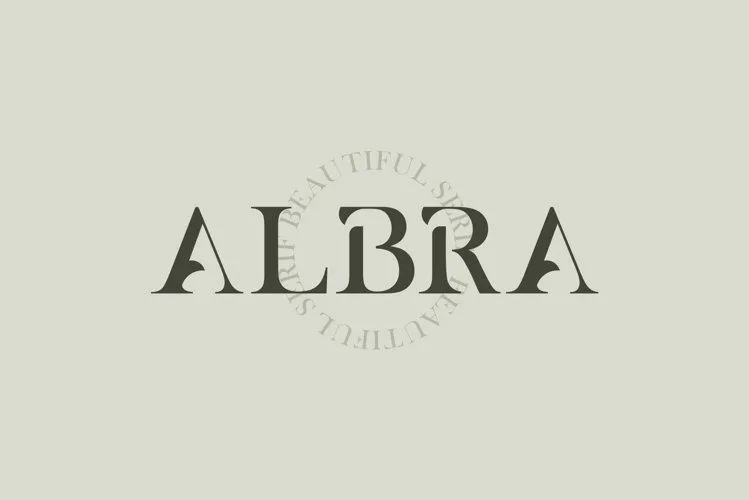
A Albra Font é uma tipografia serif inspirada nas kana hiragana, criada pelo designer Vroz Studio. Esta fonte é perfeita para uma variedade de projetos, desde editoriais e revistas até invitations de casamento e postais de aniversário. Ideal para se adequar a estilos variados como moda, branding, fotografia e design de blog. A Albra Font também brilha em aplicativos digitais, tais como websites e blogs. Seja você um designer gráfico ou editor de fotos, a Albra oferece flexibilidade para personalizar e adaptá-la a diversas necessidades. Além disso, sua elegância e detalhes sutis garantem um toque refinado a qualquer projeto que escolha aplicar. Compreender os diferentes usos desta fonte pode transformar suas criações digitais em algo realmente especial.